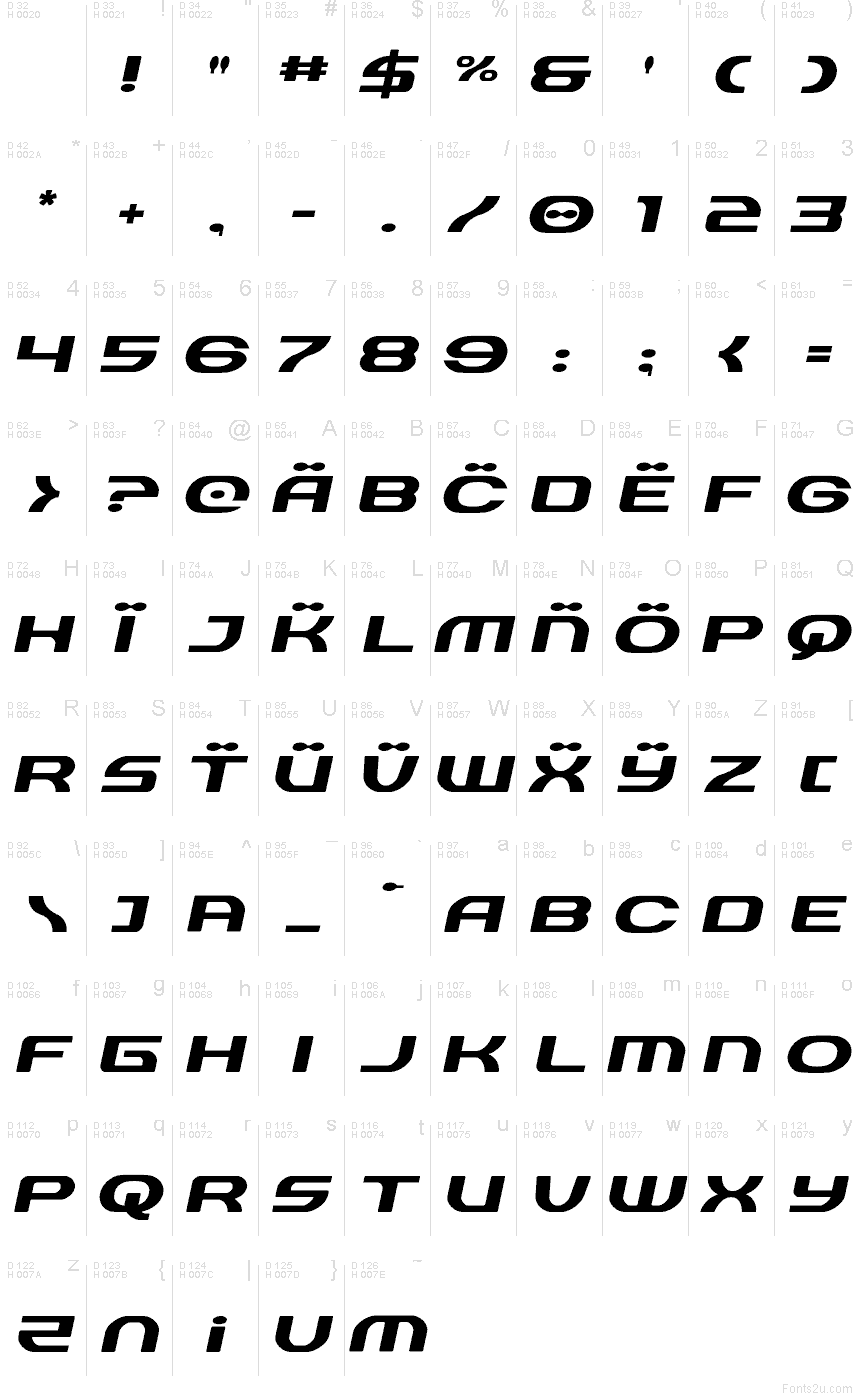
vOiture Italic par Iconian Fonts est une police d'affichage futuriste gratuite dotée de larges lettres penchées vers l'avant, de courbes amples et d'extrémités nettement tranchées qui rappellent des emblèmes automobiles personnalisés. Sa silhouette basse et solide dégage une impression de vitesse et de mécanique.
Les courbes aérodynamiques font directement écho à la carrosserie des véhicules, de sorte que le lettrage peut faire partie intégrante du concept graphique dans l'image de marque automobile, les affiches de course et les interfaces de jeux de conduite, plutôt que de paraître comme une simple légende ou une étiquette séparée. Cette même construction profilée convient également aux vêtements de sports mécaniques, où sa masse solide et ses angles coupés relient la typographie aux livrées de course, au matériel de haute performance et à la culture visuelle des voitures modifiées.
vOiture Italic